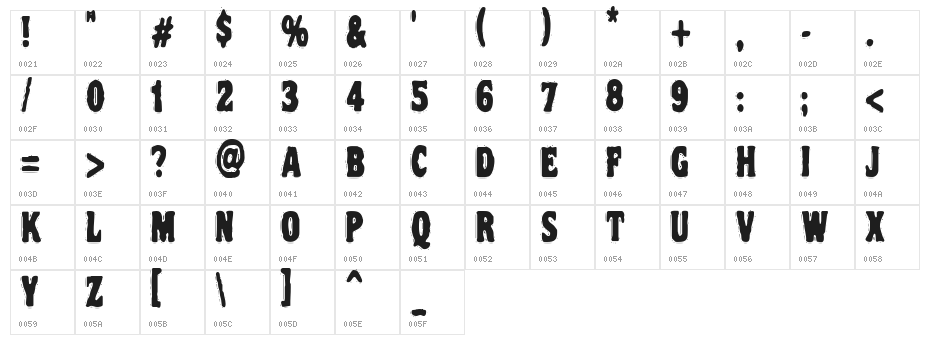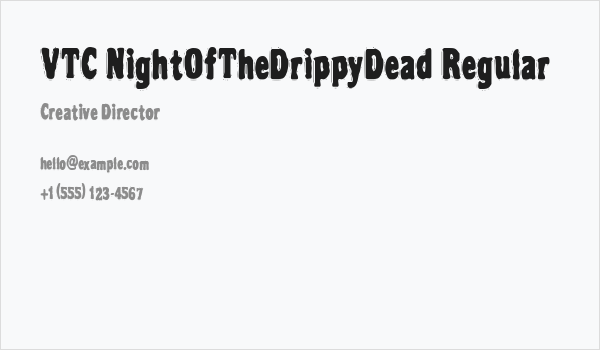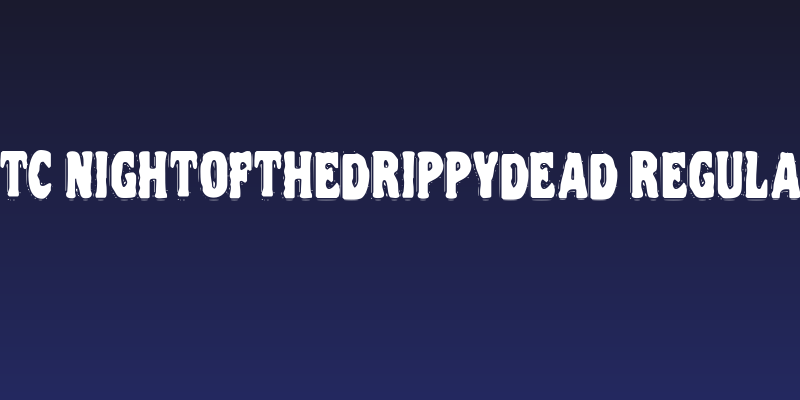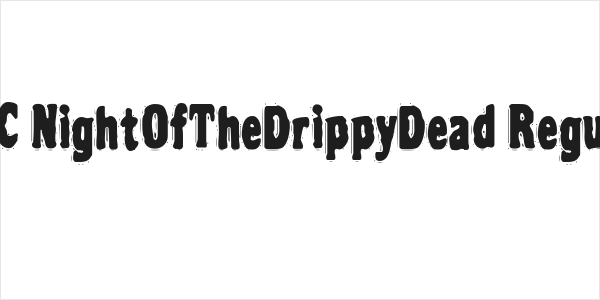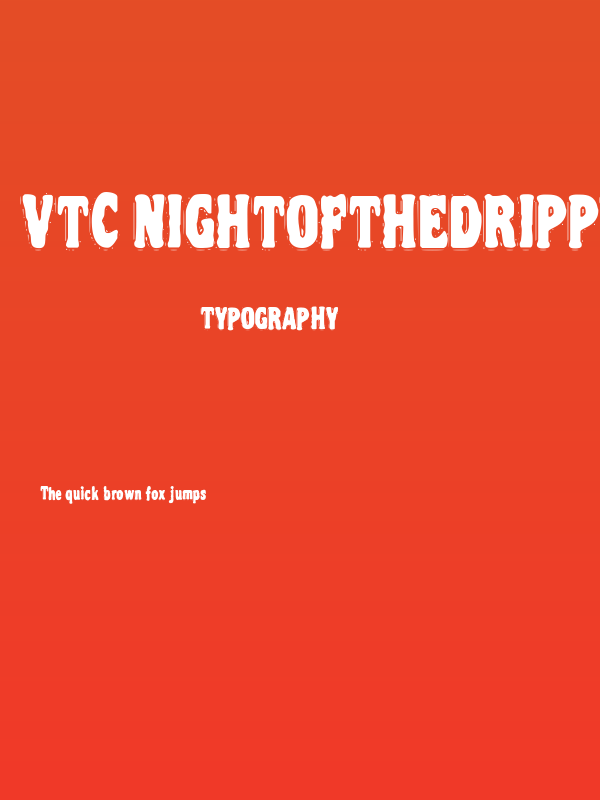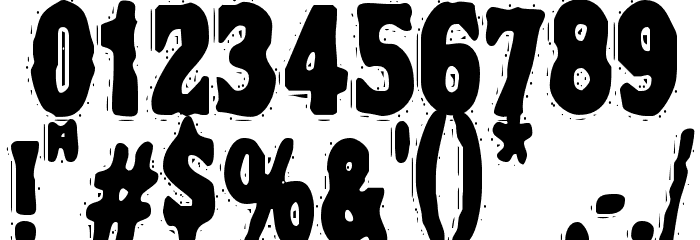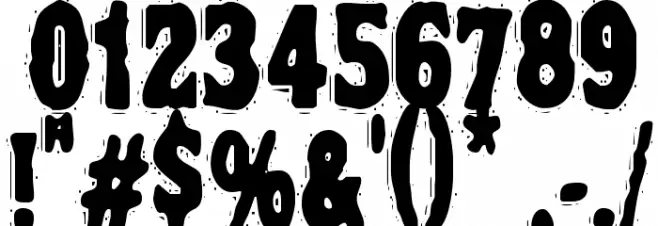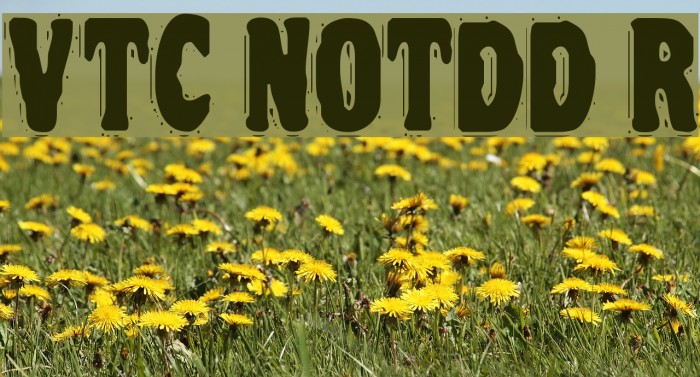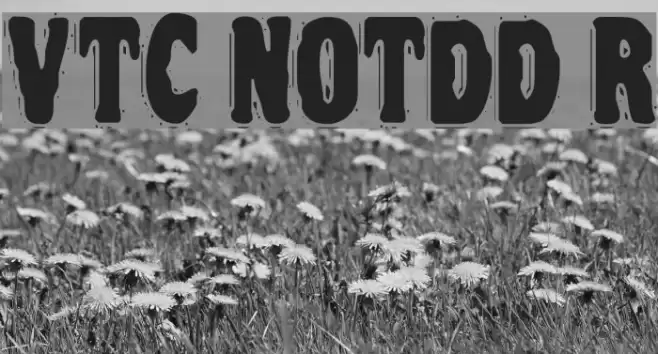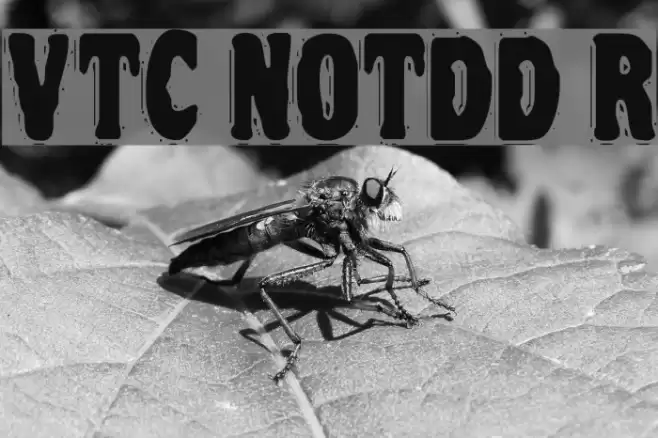
VTC NightOfTheDrippyDead Regular Font
| Vorgeschlagene Projekte | Ideal for Halloween invitations, horror movie posters, themed party decorations, and playful branding. |